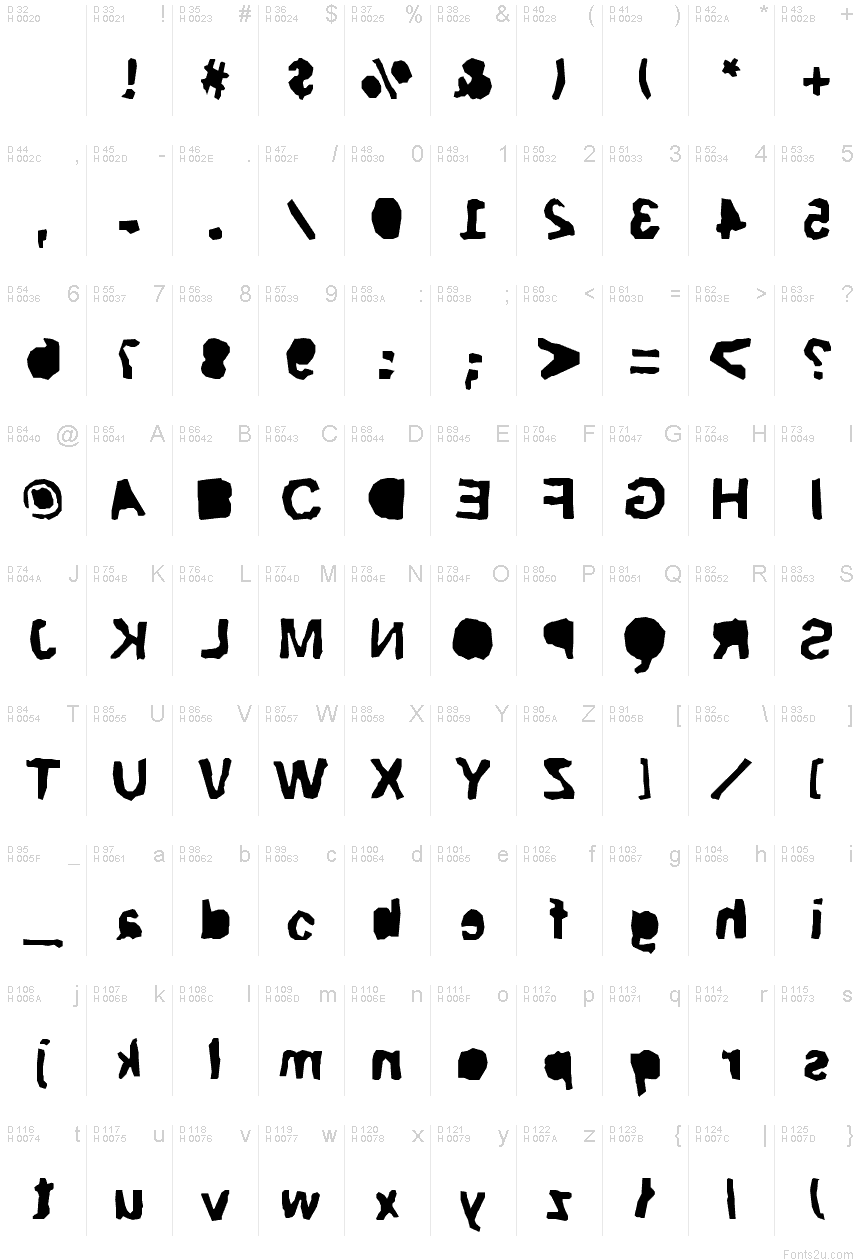
rip TRASH Cut von Manuel Viergutz ist eine kostenlose, zerstörte Display-Schrift, die aus stumpfen, zerrissen wirkenden Formen aufgebaut ist. Ihre ungleichen Kanten und abrupten Schnitte lassen die Buchstaben wie aus schwerem Papier herausgeschnittene Fetzen wirken.
Ein Musikplakat ist ihr stärkstes Umfeld, besonders für Punk-, Noise- oder Industrial-Acts. Dieselbe rohe Silhouette passt zu Band-Merchandise und Untergrund-Event-Flyern, wo die Schriften wie Collage-Material wirken können. Sie spricht vor allem DIY-Musikpublikum und Designer an, die sich zu fotokopierten Grafiken hingezogen fühlen.
rip TRASH
- Styles: regular, mirror, cut, cutMIRROR, round, roundMIRROR